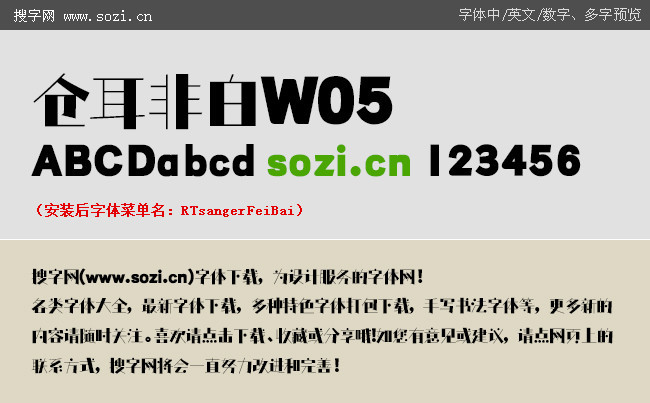
倉耳非白W05
搜字網(wǎng)提供一倉耳非白W05中文藝術(shù)字體下載,倉耳非白是一款粗細(xì)對比明顯、風(fēng)格強烈、擁有5個字重的家族字體,結(jié)構(gòu)方整,筆形簡潔、利落,帶有明顯區(qū)別于其他字體的風(fēng)格。是倉耳字庫推出的一款支持全領(lǐng)域永久免費商用的個性藝術(shù)字體。